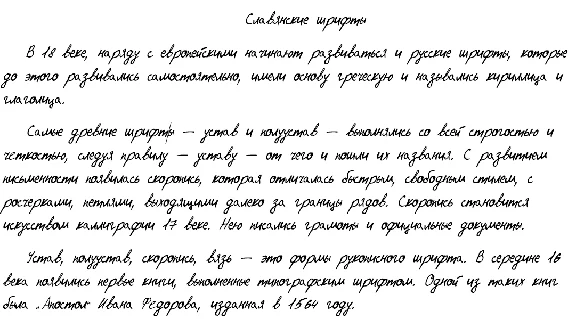
Мужской рукописный шрифт из почерка jeDy's font
- Авторский шрифт из мужского почерка для написания рефератов, докладов, курсовых, дипломов, лекций и т.д. на русском языке.
- Поддержка только русского языка.
- Тип ручки: гелевая
- Рекомендуемый размер букв: 16-20пт
- Поддержка только русского языка.
- Тип ручки: гелевая
- Рекомендуемый размер букв: 16-20пт